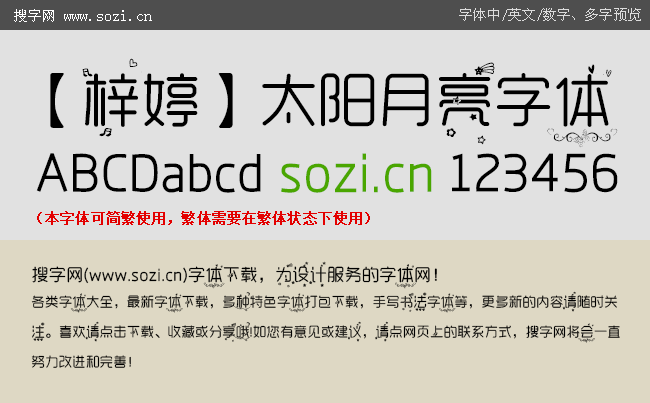
太陽月亮字體
搜字網(wǎng)給大家提供一款很有趣的手機(jī)中文字體下載。我愛邊伯賢字體,這款手機(jī)字體是在造字工房悅黑體字體筆畫間插入了可愛星星和月亮等卡通花紋圖案。趣味性實(shí)足,該手機(jī)字體個(gè)性實(shí)足,趣味性強(qiáng),又保持了文字的識(shí)別度,特別適合喜歡手機(jī)字體個(gè)性一些的朋友在手機(jī)上安裝使用。